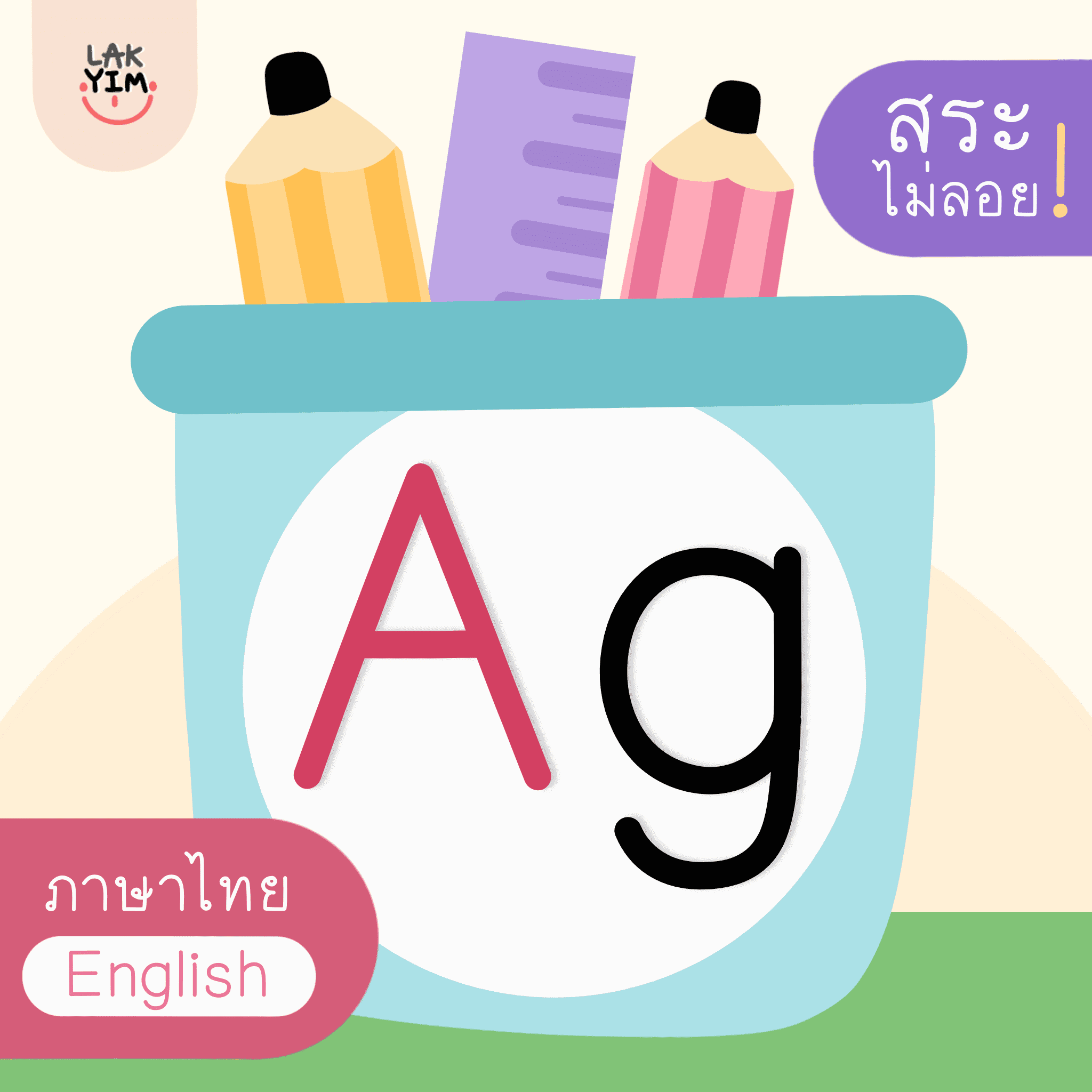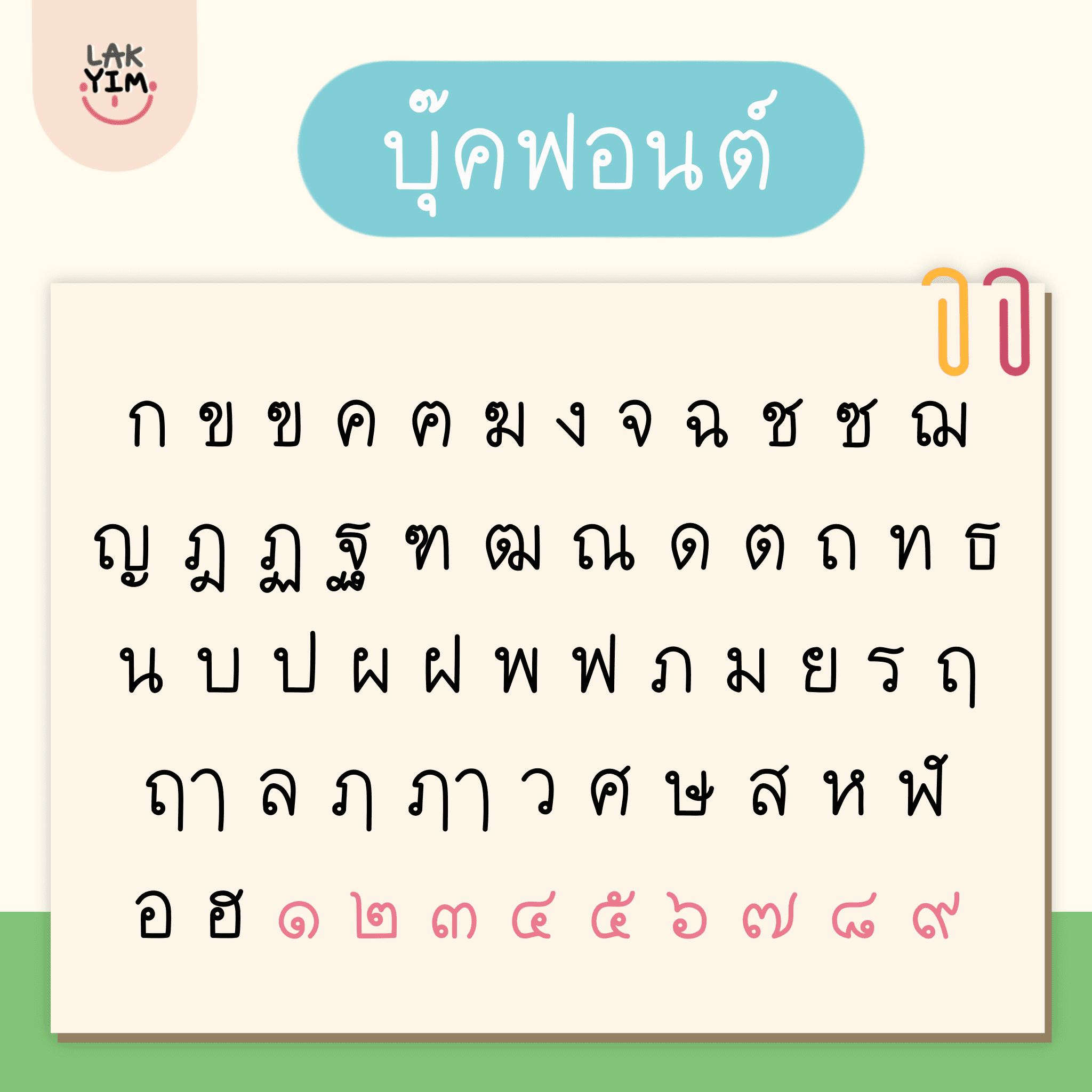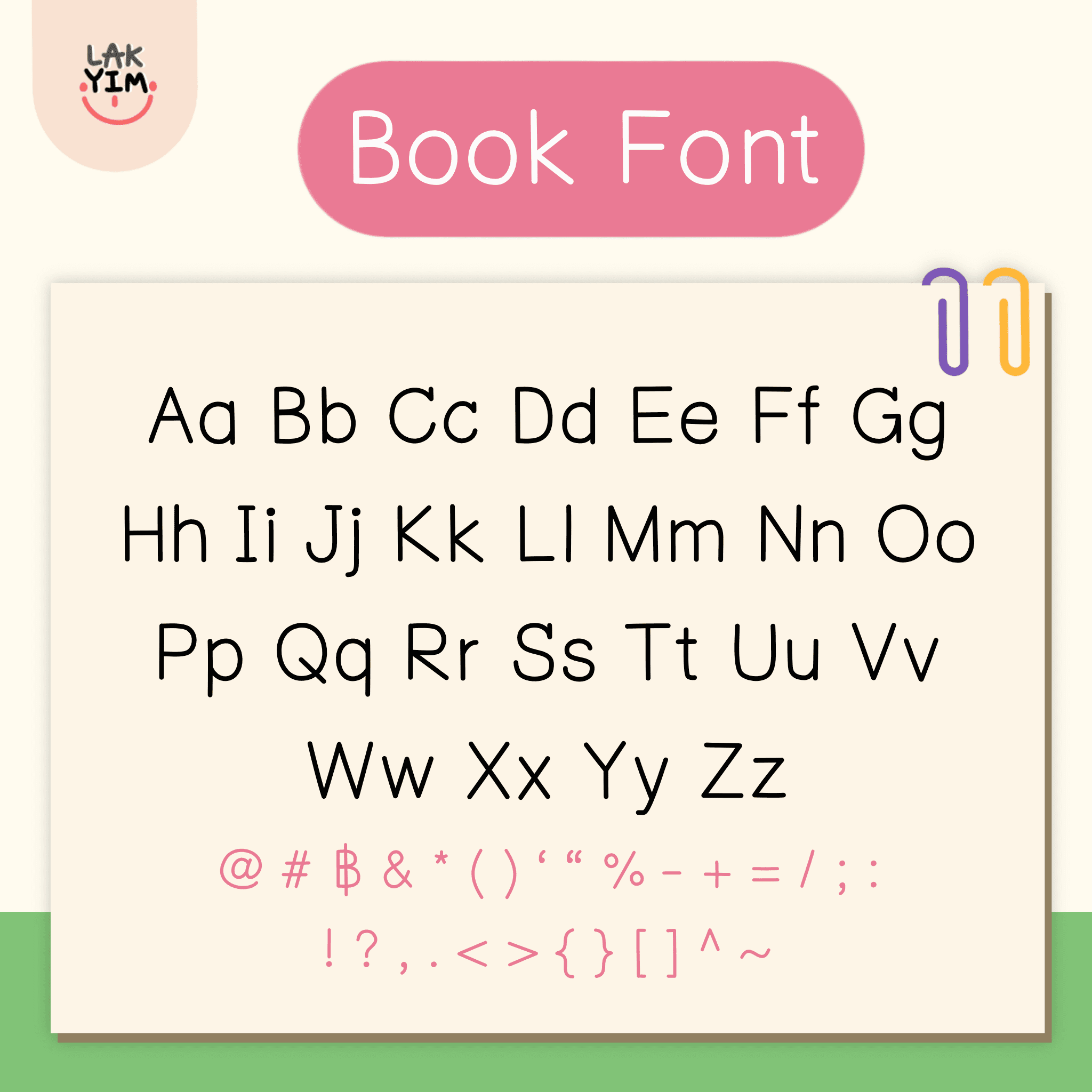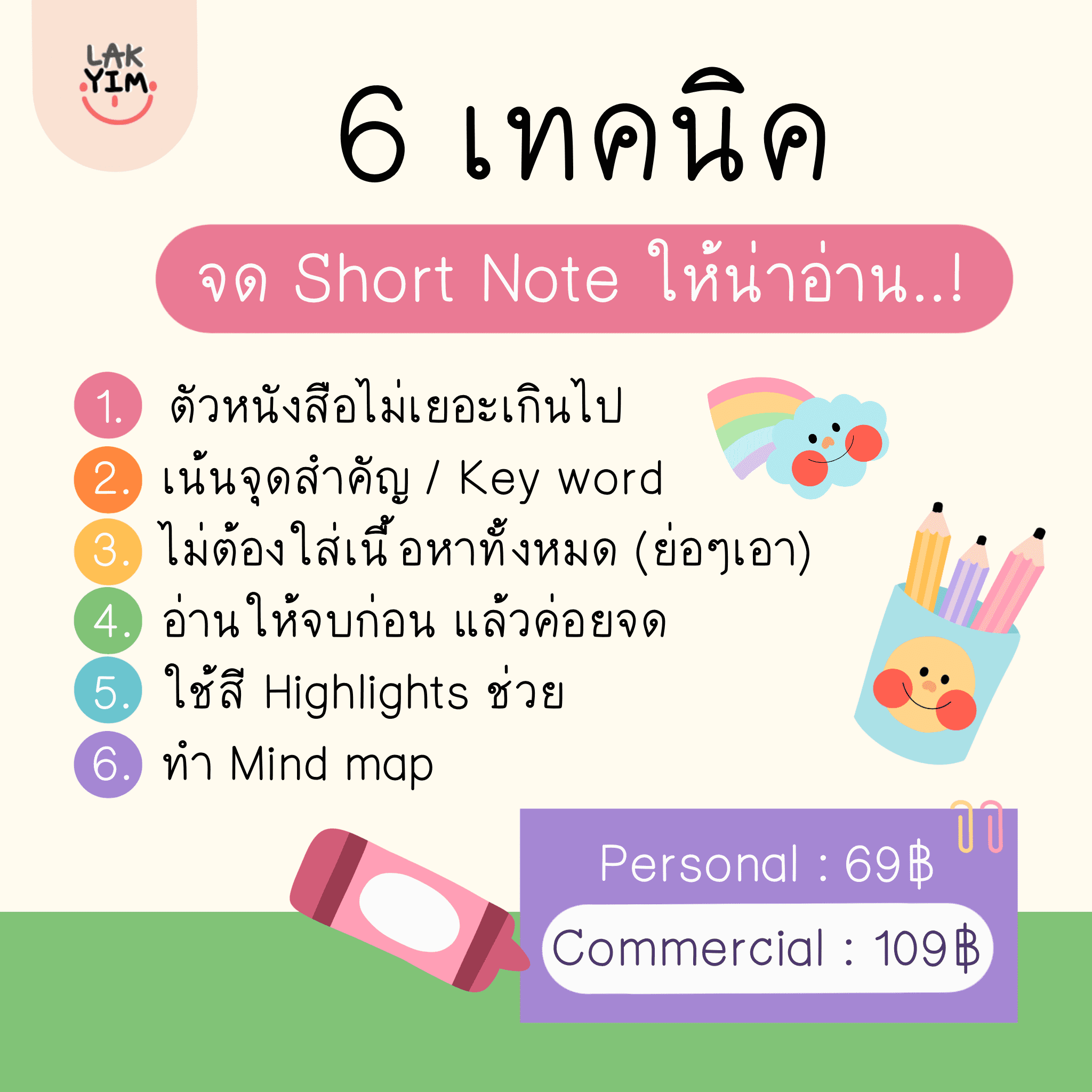
LAKYIM.OFFICIAL | FONT (BOOK Font)
ฟอนต์ลายมือให้ความรู้สึกเหมือนคัดลายมือสุด ๆ
เป็นระเบียบ อ่านง่าย สบายตา เหมาะกับการเอาไปใช้เขียนบันทึก หรือทำชีทสรุปที่สุด
📍สระ ไม่ ลอย ‼️‼️
– มีทั้งภาษาไทยและภาษาอังกฤษ